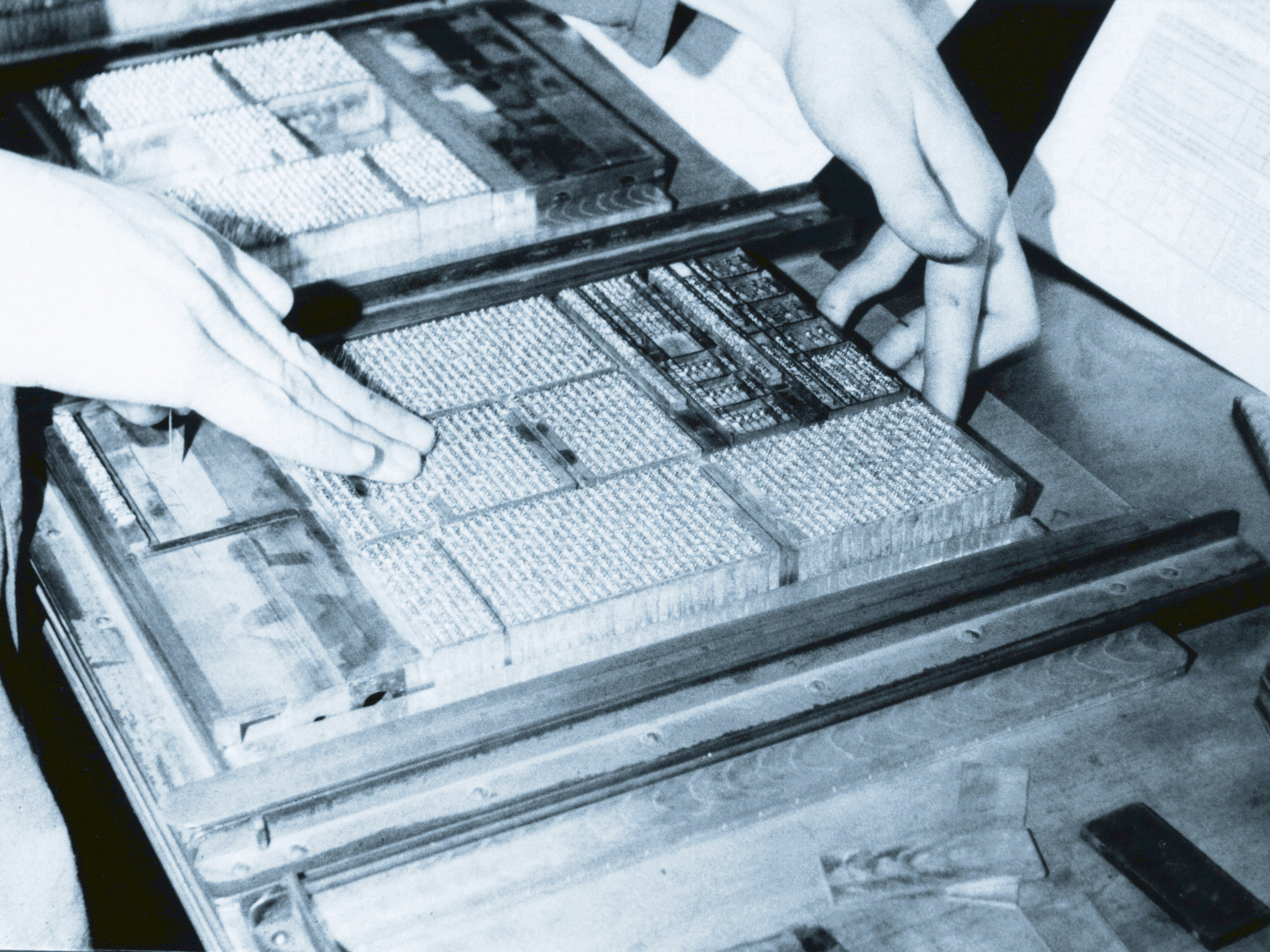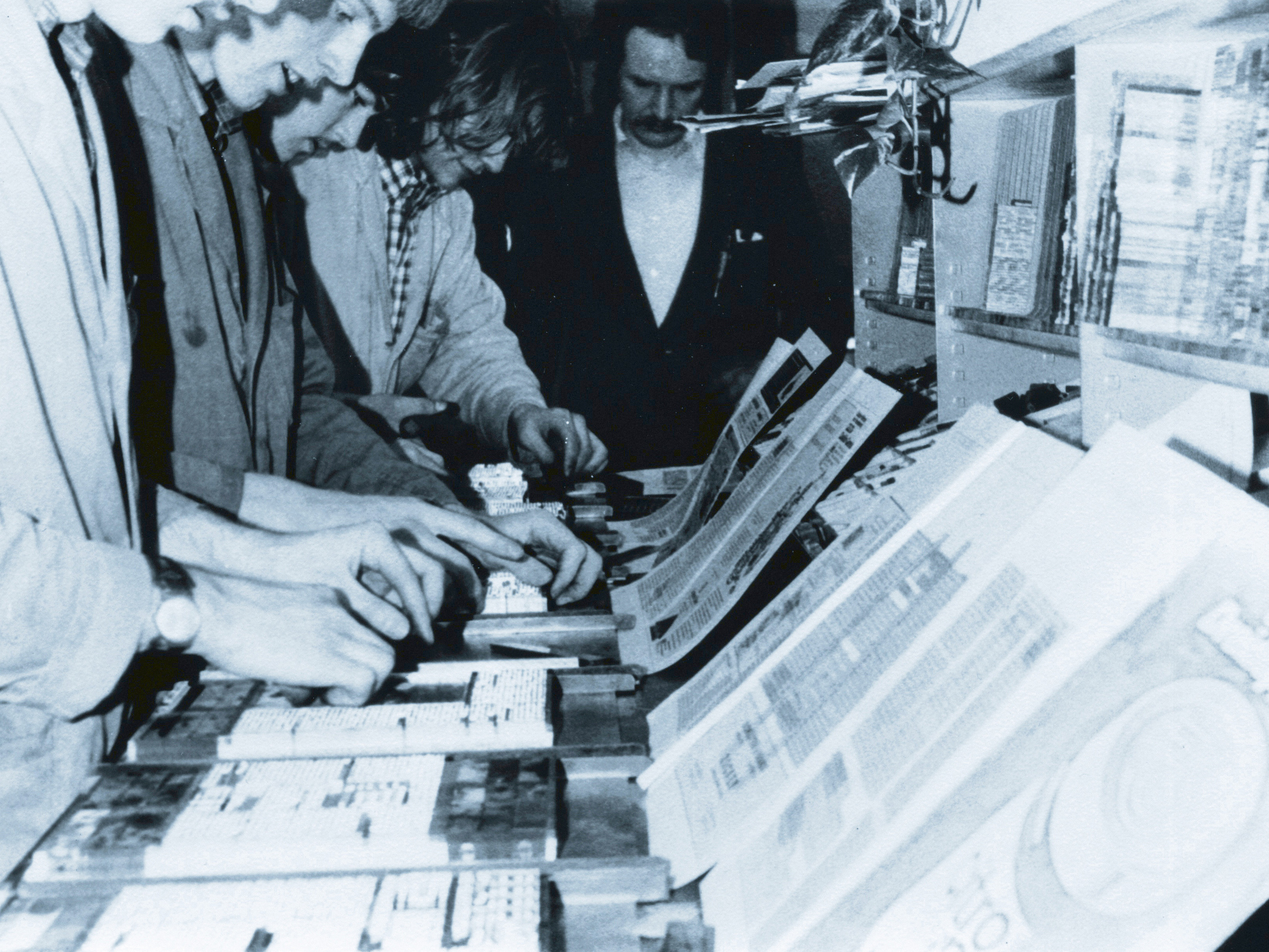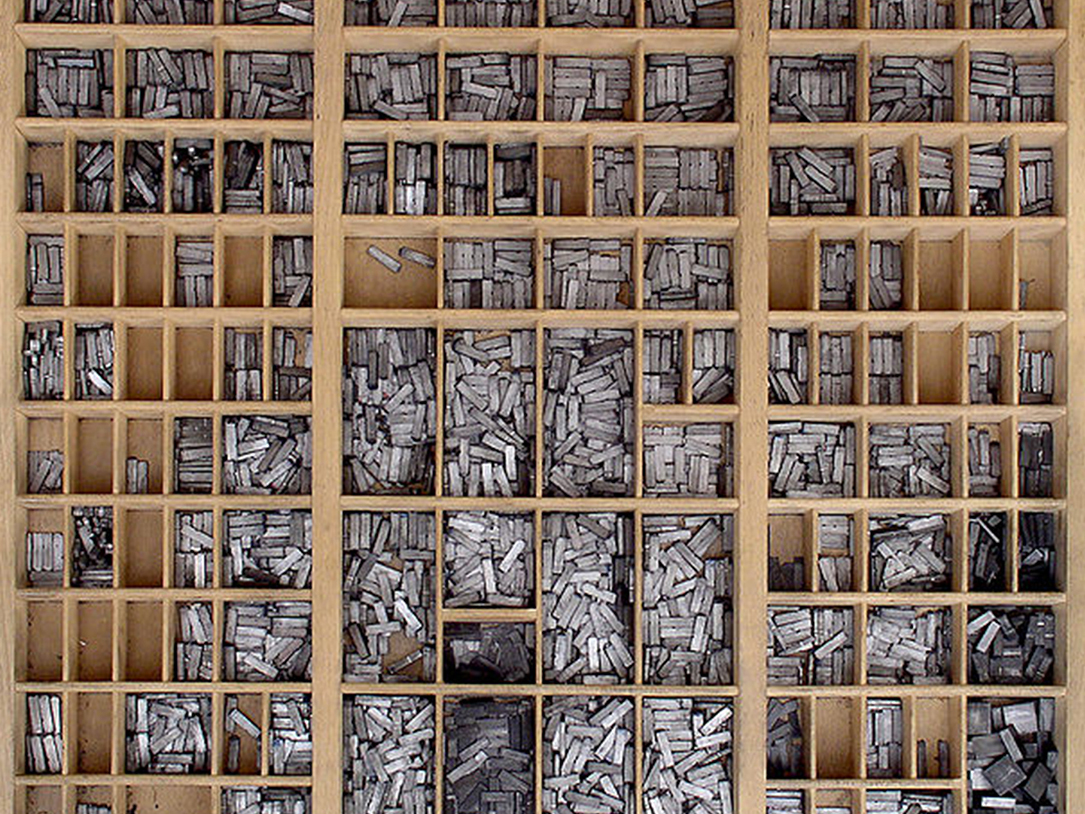
Bleisatz und Buchdruck wie Gutenberg: Foto-Fundstücke aus meiner Schriftsetzer-Lehre
Am Wochenende war es mal wieder Zeit für den Frühjahrsputz auf meinem Rechner (mache ich jedes Jahr). Dabei finden sich immer allerlei Bilder und Geschichten, die man so schnell nicht vergessen möchte. Diesmal habe ich einige Bilder aus meiner Berufsausbildung als Schriftsetzer im Bleisatz entdeckt. Die Fotos entstanden 1975 und zeigen meine ersten Monate in einem Handwerk, das mich für den Rest meines Lebens begleiten und prägen sollte.
Uwe Steinacker in seiner Schriftsetzer-Lehre
Ein junger Uwe Steinacker als Schriftsetzer im 2. Lehrjahr vor dem Setzkasten nach DIN 16 518 (DIN 16 518 regelt das in Deutschland gebräuchliche Klassifizierungssystem von Schriftarten).
Zum Thema Setzkasten: Eine gute Akzidenz-Setzerei wollte in der damaligen Zeit beispielsweise aus neun Schriftgruppen circa 50 verschiedene Schriftarten anbieten. Im Idealfall hatte die Setzerei drei bis sechs Schriftschnitte in den Graden von 6 bis 48 Punkt im Angebot – und damit hunderte von Setzkästen wie abgebildet. Hinzu kamen weitere Materialien wie Linien, Symbole, Regletten für den Durchschuß (Zeilenabstand) oder Blindmaterial für das Ausschließen von Textzeilen im Block- und Flattersatz.
Ein Setzkasten mit Bleilettern im Bleisatzhandwerk
Hier ein Ausschnitt aus dem Setzkasten. Kaum vorstellbar: Jeder Setzkasten enthält nur eine einzige Schriftgröße einer einzigen Schriftart!
Im ersten Lehrjahr lernte ich außerdem eine neue Tierart kennen, die Bleiläuse. Ältere Setzer übergossen den Bleisatz mit Wasser, um das Ungeziefer aus den winzigen Ritzen hervorzulocken. Ging nun der Unerfahrene (zum Beispiel ich) zu nah an den Satz heran, um diese Tierchen näher zu studieren, quetschte der Kollege den Bleisatz schlagartig zusammen. Das eklige Resultat: Die Bleiläuse und Wasserspritzer schossen dem Pechvogel mit großer Wucht ins Gesicht (davon gibt es zum Glück kein Bild).
Auf den folgenden Bildern sehen Sie die (Setzer)Lehrlinge bei der Arbeit. Mit strengem Auge wacht der Metteur (der Schriftsetzer, der aus gesetzten Texten die Seiten für den Druck gestaltet), dass Umbruch und Reihenfolge der Satzspalten richtig angeordnet werden.
Schriftsetzer-Lehrlinge bei der Arbeit
Die Schriftsetzer-Lehrlinge in der Setzerei beim Umbruch von Maschinensatz.
Gesetzter Text im Bleisatzhandwerk
Nahaufnahme einer händisch gesetzten Meisterleistung 😉